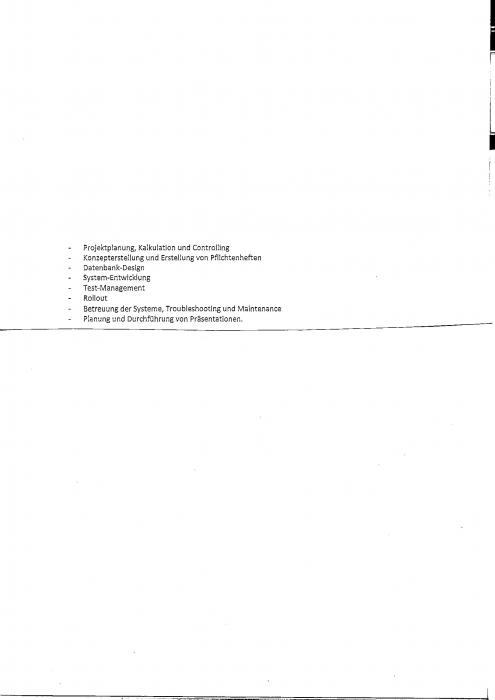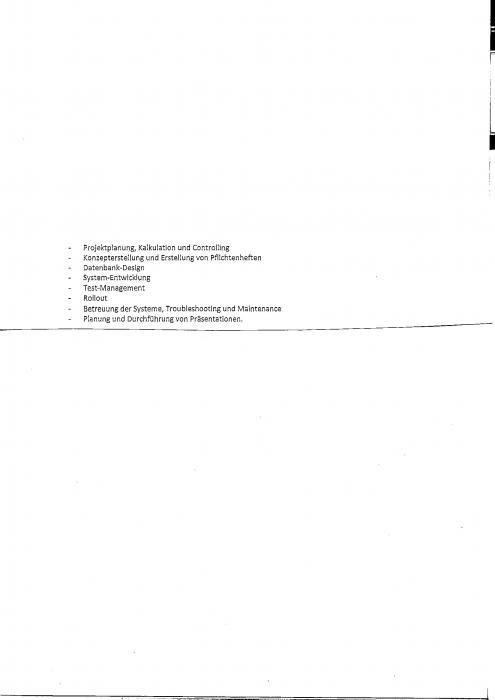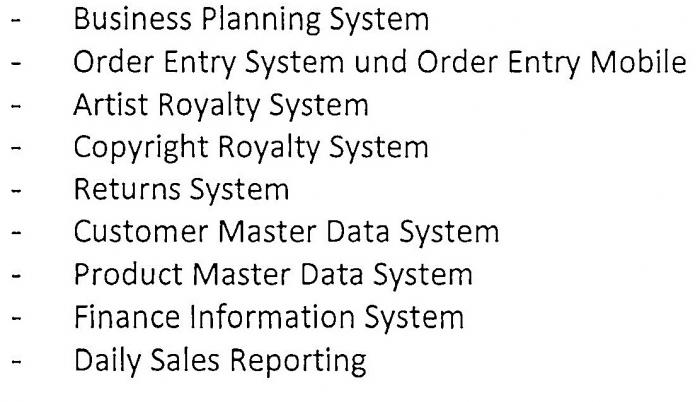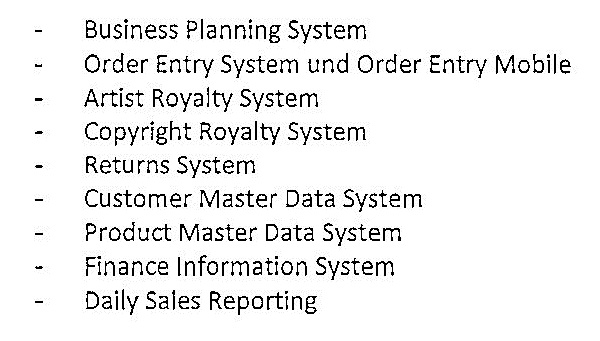
Bin auf der Suche nach der Schrift in der anbei gefügten Datei
meines erachtens ist es ausgeschlossen, auf der basis einer so winzigen abbildung zuverlässig die schriftart zu identifizieren. schuss ins blaue:
wenn du genaueres wissen willst, bräuchten wir eine abbildung, in der deutlich stärker auf die buchstaben eingezoomt wurde.
Ist die neue Datei für den Zweck ausreichend? Danke :-)
die größe ist prima, aber der scan (bzw. die zugrundeliegende abbildung) ist einfach sehr grobkörnig. da lassen sich details schwer erkennen. ich würde daher bei meinem ersten tipp bleiben: calibri. die liste sieht aus wie etwas, das jemand mit den standardeinstellungen in word runtergeschrieben hat. das spricht für einen gängigen systemfont. wenn ich mir die buchstabenformen, soweit erkennbar, anschaue, ist da auch nichts dabei, das mit calibri inkompatibel wäre. es scheint, als sei die laufweite etwas geringer als bei calibri, aber bei einem tracking von −9 deckt sich calibri mit der vorlage praktisch komplett.
das Beispiel sieht für mich nach einer amerikanischen Groteskschrift aus. Vielleicht irgendwas in Richtung NewsGothic, FranklinGothic. Open Sans, Lato oder Source Sans Pro könnten auch passen.
Herzlichen Dank! ich habe erneut eine Datei hochgeladen mit 400 dpi Auflösung.
Bleibt es dabei?